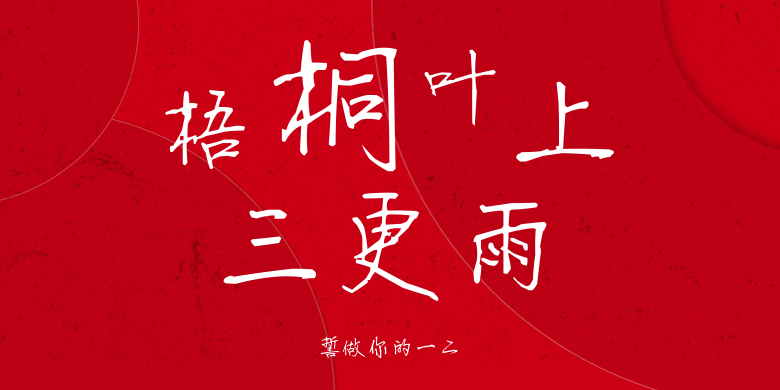
誓做你的一二
誓做你的一二,这款字体结构工整、笔画清晰,兼顾美观与易读性,适用于标题、正文、海报、包装、LOGO 等多种场景。字形优雅稳定,风格百搭耐看,适配日常排版与创意设计,让文字呈现更舒适、更具质感。誓做你的一二一笔一画,皆是细节,以均衡的比例、流畅的线条打造舒适视觉体验,字形端正大气,风格简约现代。无论是商业设计、品牌宣传还是日常排版,都能轻松驾驭,让文字更有格调与力量。誓做你的一二字体下载。